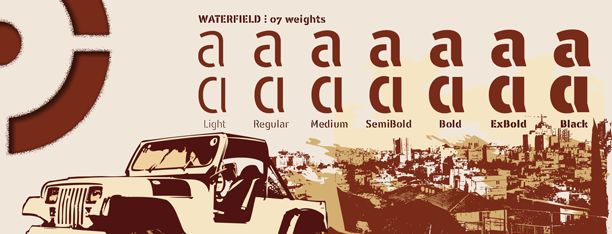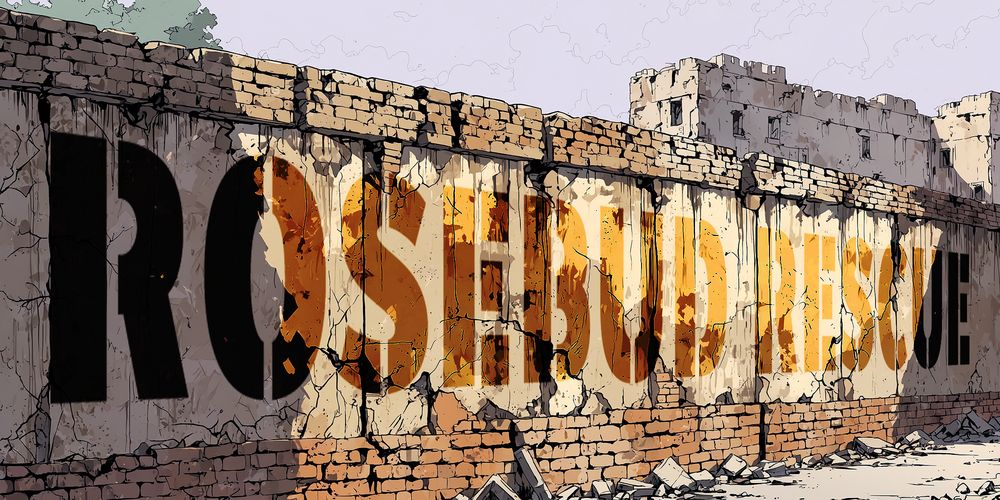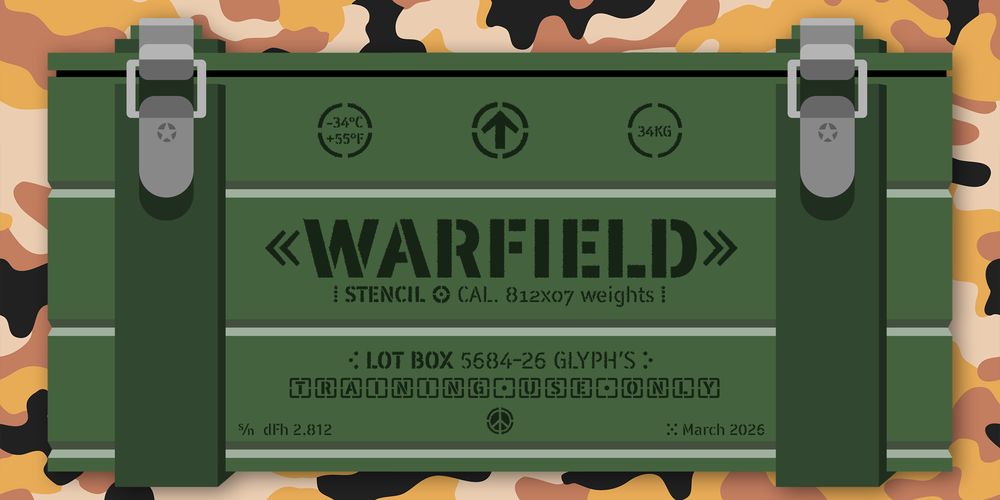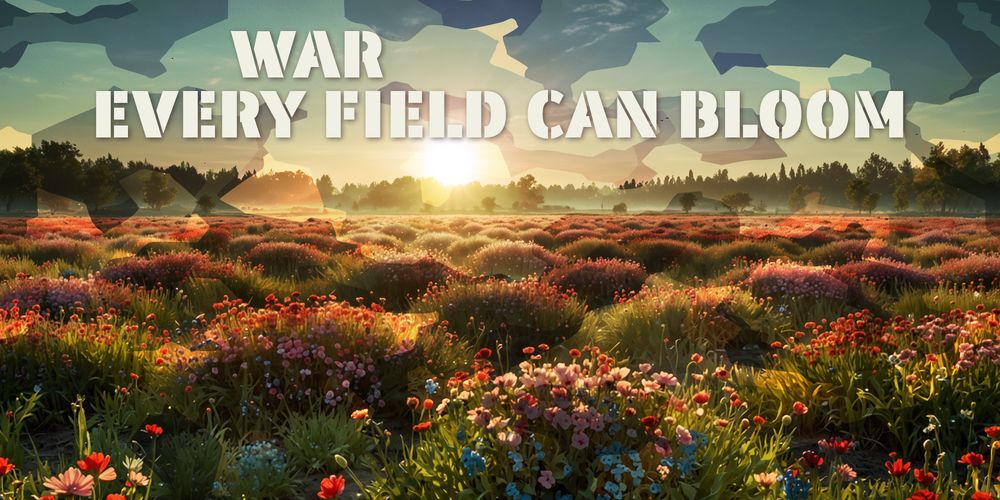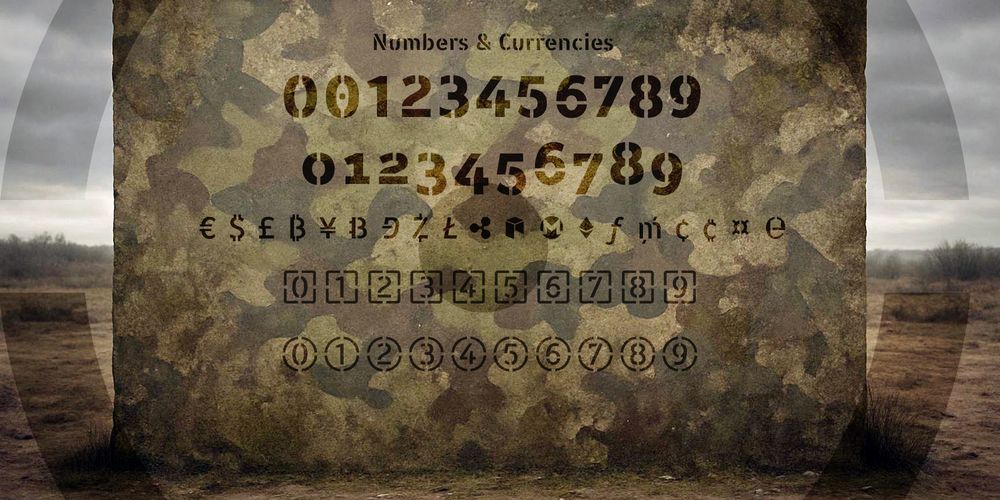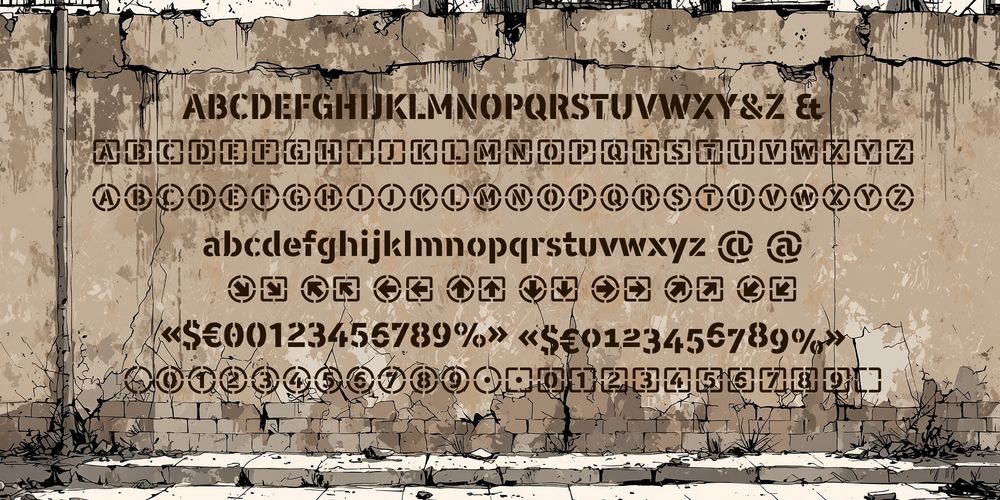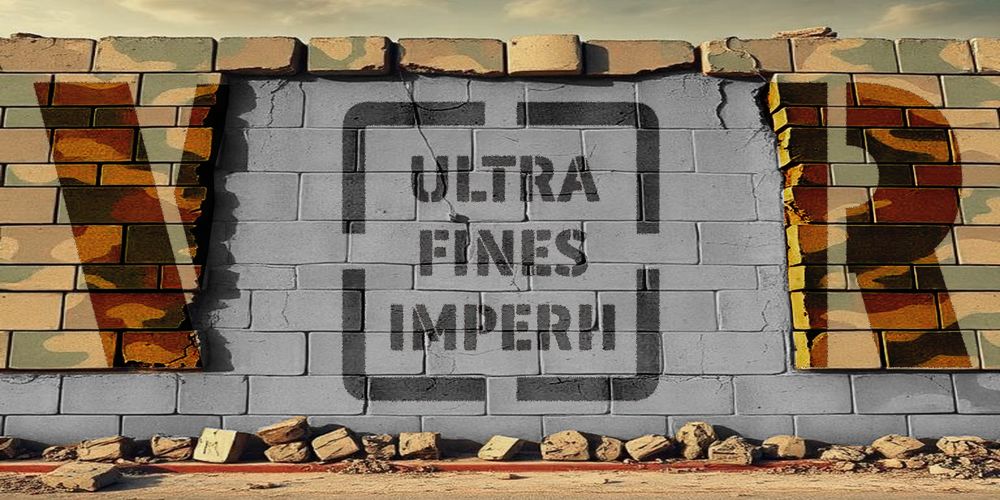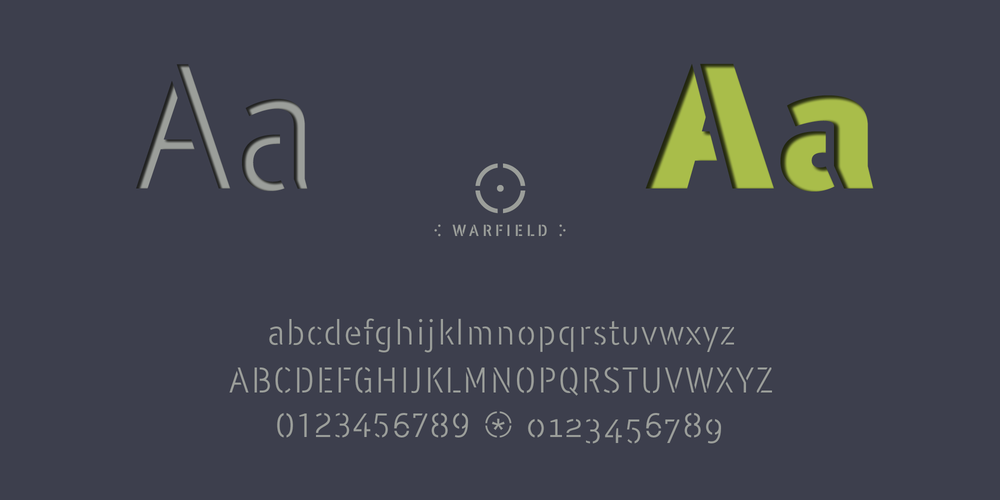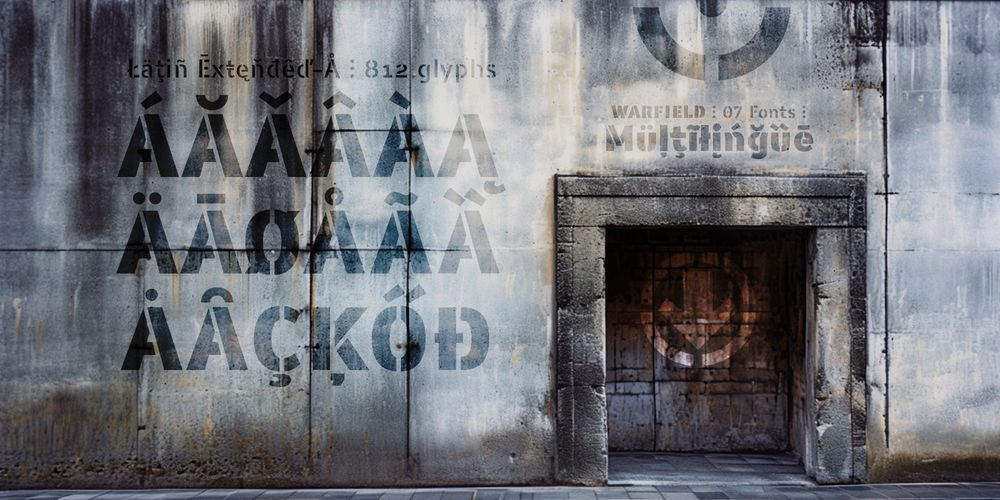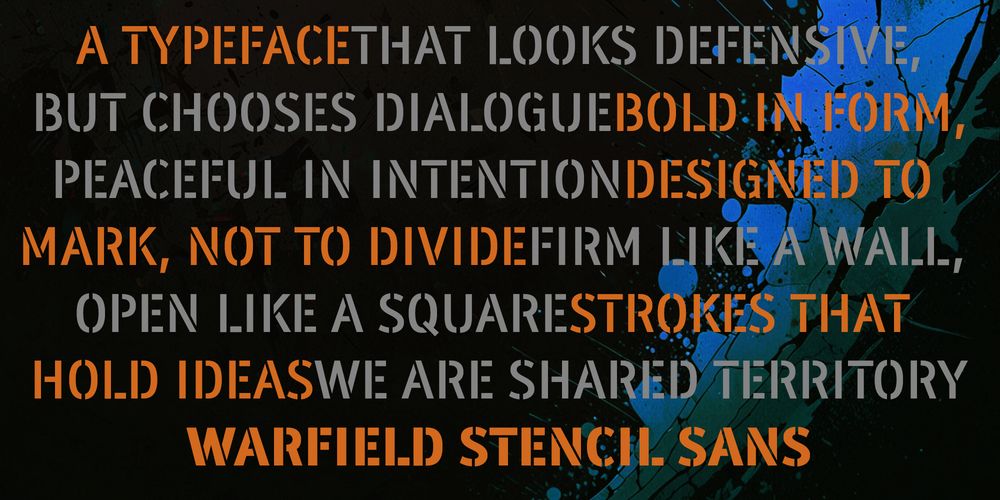
Es Sans Serif, sí, contemporánea que no solo se lee, sino que se siente, llevando con orgullo los cortes, los puentes y las interrupciones que la definen, dándole un porte recto y solemne.
Estilo: Stencil, Sans Serif, Display, Army, Militar
Proporción: Light, Regular, Medium, Semi Bold, Bold, Extra Bold, Black
Glyphs: 812
Alternates: 219
Latin-Extended: Latín Básico, Europa Occidental, Central & Oriental.
812 glyphs w/ 219 alternates: Numbers & Letters
Las tipografías Stencil, esas criaturas nacidas de la necesidad industrial y la urgencia militar, siempre han tenido esa potencia. Son las letras de las cajas de munición y los muros de hormigón, el alfabeto de lo práctico, de lo inmediato. Pero, ¿y si ese grito pudiera también susurrar? ¿Y si la dureza del acero pudiera albergar un corazón?
La estética de la precisión
WARFIELD es, por definición, una tipografía esténcil, bebe de la herencia militar e industrial, pero se desprende de la agresividad para abrazar la legibilidad absoluta.
Es Sans Serif, sí, contemporánea que no solo se lee, sino que se siente, llevando con orgullo los cortes, los puentes y las interrupciones que la definen, dándole un porte recto y solemne.
Desde la sutileza etérea de la Light hasta la autoridad rotunda de la Black, WARFIELD recorre 7 pesos diseñados para resistir cualquier batalla creativa y modular el tono de voz. WARFIELD muta según tu intención:
- Light — Elegancia táctica, sutileza con estructura
- Regular — El equilibrio perfecto entre forma y función
- Medium — Presencia sin agresión
- Semi Bold — Autoridad con refinamiento
- Bold — Comunicación que exige atención
- Extra Bold — Impacto controlado
- Black — La máxima expresión de peso visual
Cada peso mantiene la integridad del sistema stencil y una legibilidad excepcional. Diseñé cada corte con precisión para que la lectura sea limpia, incluso en tamaños pequeños o contextos exigentes. Quería contundencia, pero también control. Mi objetivo no era crear una fuente, sino un ecosistema.
Un arsenal creativo sin precedentes
Una caja de Pandora llena de funciones avanzadas Open Type. Aquí es donde la cosa se vuelve existencialmente divertida.
- Diversidad Estructural: 03 juegos de mayúsculas y 05 de minúsculas que permiten una textura tipográfica orgánica y dinámica. 15 personalidades en una sola familia.
- Precisión Científica: 06 juegos de números y funciones avanzadas para fórmulas y fracciones impecables (ordinales, denominadores, numeradores e inferiores científicos).
- Simbolismo y Dirección: un inventario completo de flechas (porque siempre hay que señalar el camino), símbolos monetarios de aquí y de allá, y hasta de las principales criptomonedas. Porque el pasado y el futuro deben convivir en un mismo teclado.
- Anotaciones Avanzadas: Formas circulares y cuadradas para letras y números, perfectas para señalética o énfasis visual.
- Alternativas contextuales y ligaduras estándar y discrecionales — 219 caracteres y signos alternativos — libertad creativa real
- Misticismo tipográfico: Sumérgete en mis signos de puntuación decorativos: el enigmático Tricolon, la rareza del Reference Mark, o la geometría sagrada del Dotted Cross y el Five Dot Punctuation. El Asterism (⁂) para señalar un pasaje relevante, el Therefore (∴) y el Because (∵) para encadenar razonamientos visuales. No son solo signos, son pequeños iconos con historia.
Espíritu pacifista, fuerza industrial
A pesar de su nombre y su armadura técnica, WARFIELD tiene un espíritu profundamente pacifista. Es una tipografía que cree en la comunicación como el puente definitivo. Es robusta para el packaging, elegante para el diseño editorial y lo suficientemente versátil para logotipos, posters y señalización de vanguardia. Es fuerte sin estridencia. Es directa sin agresividad. Es estructura con conciencia.
Con soporte para Latin Extended-A, WARFIELD habla múltiples idiomas, eliminando fronteras y conectando ideas a través de su diseño impecable.